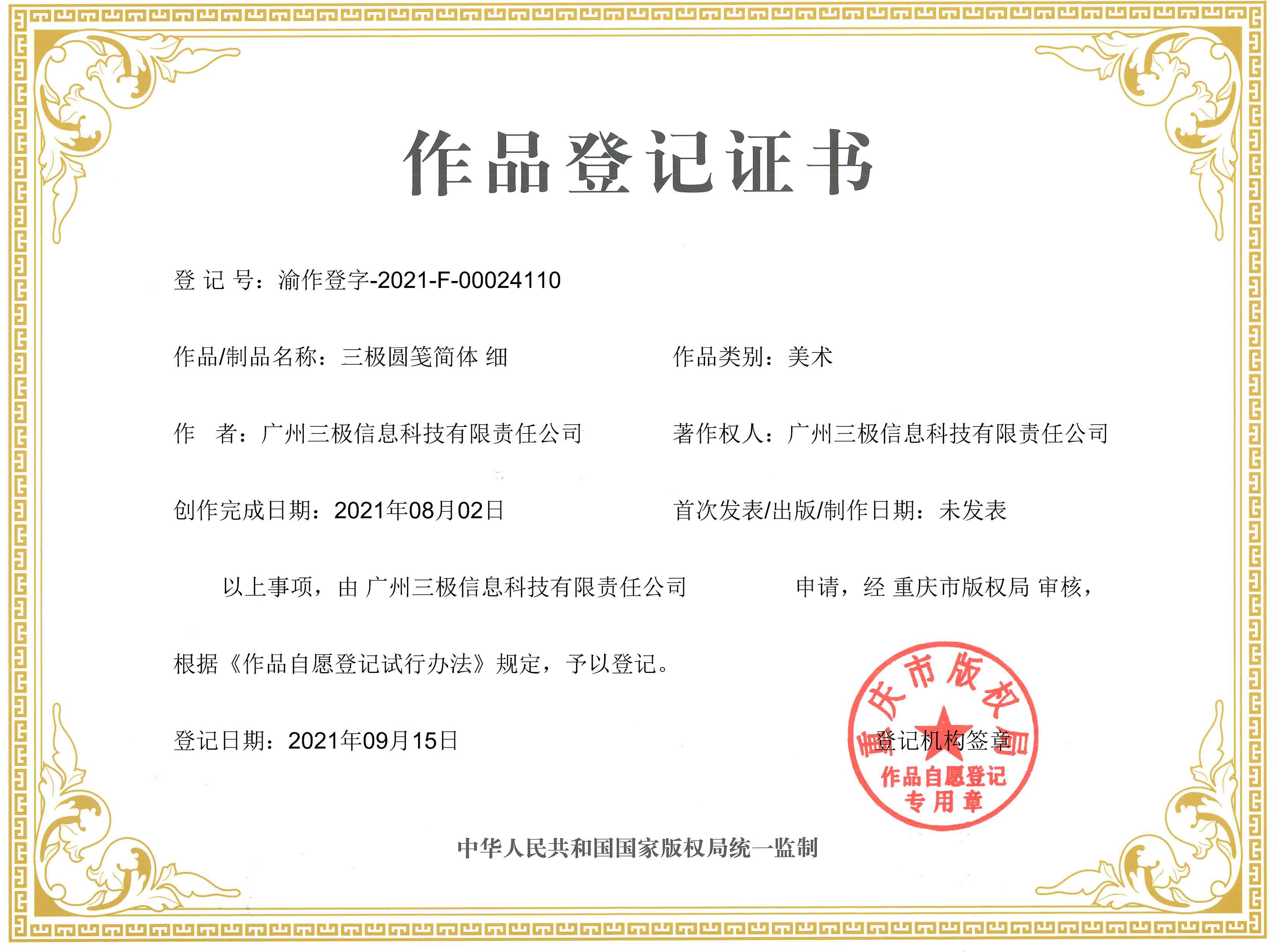
三极圆笺简体 家族
三极圆笺简体 细
三极圆笺简体 纤细
三极圆笺简体
三极圆笺简体 中粗
三极圆笺简体 粗
三极圆笺简体 超粗
字体信息
字体名称:
三极圆笺简体 细
设计师:
曾南 余艳娉 陈燕
所属分类:
创意字体
三极圆笺简体系列:这款字体的笔形由单线条构成,无多余装饰,比如口字形简化为半个圆圈,笔画断连增强装饰性。字面和重心相对一致,具有一定的易读性。形体偏圆润,趣味性十足。